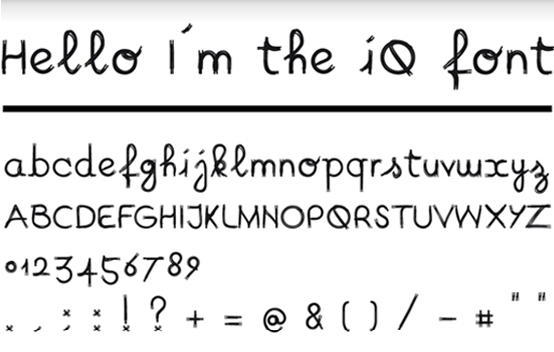
IQ Font
Hemos visto tipográfias hechas con comida, con plantas, con huesos con, con animales, esqueletos, con los instrumentos más extravagantes y demas, pero, ¿Con un Toyota?